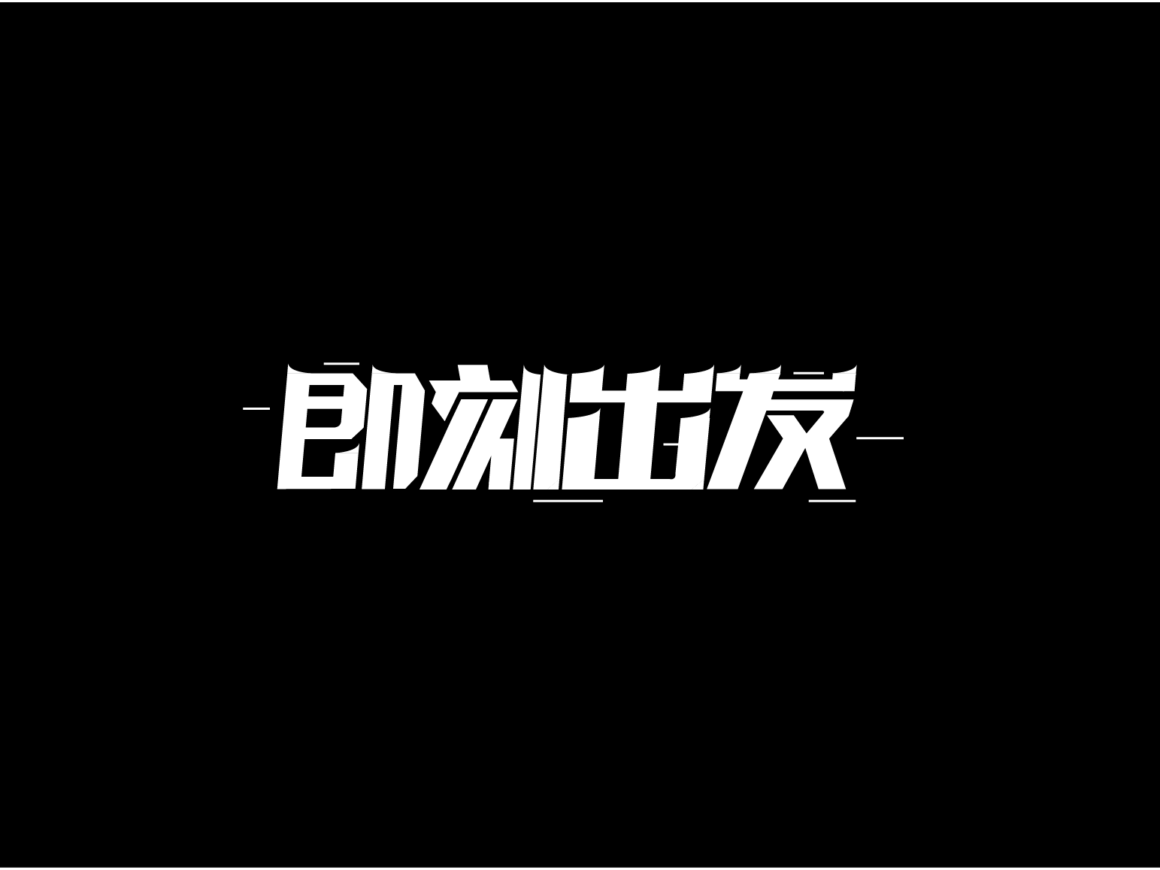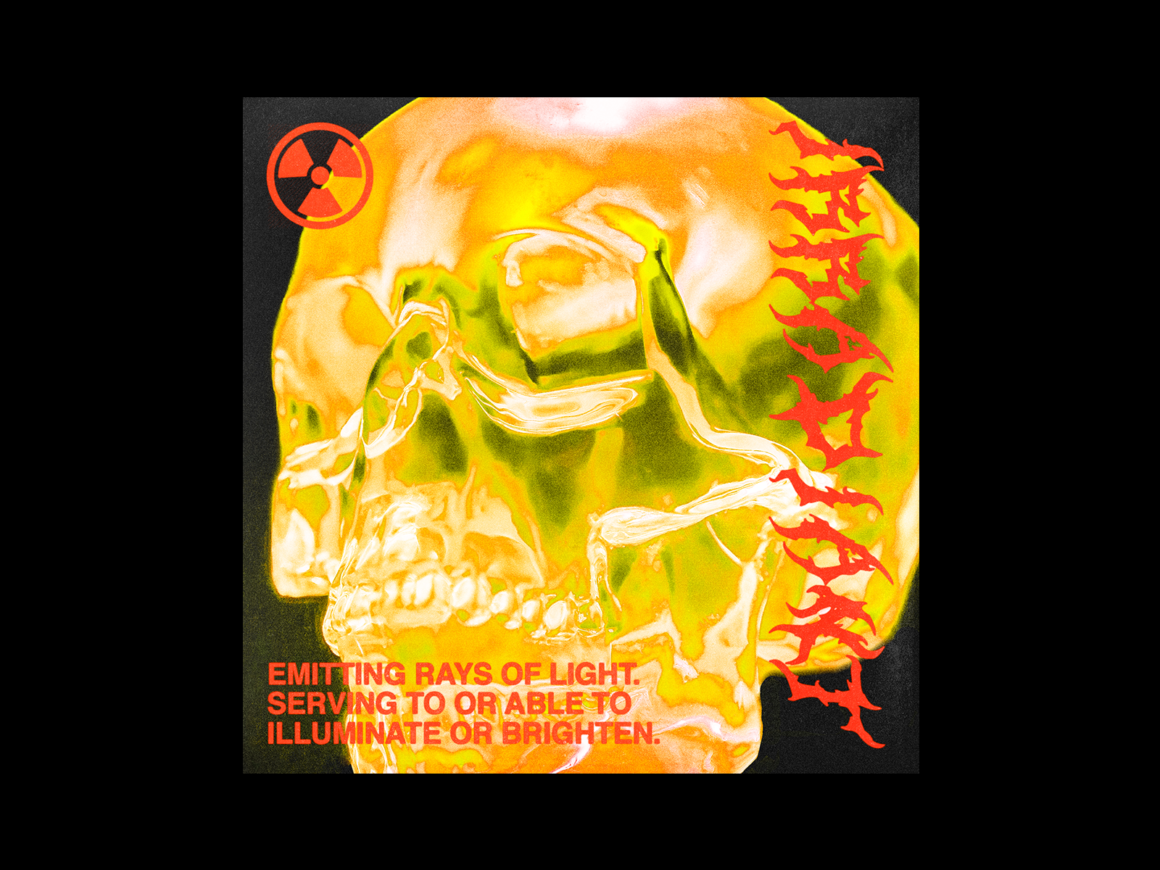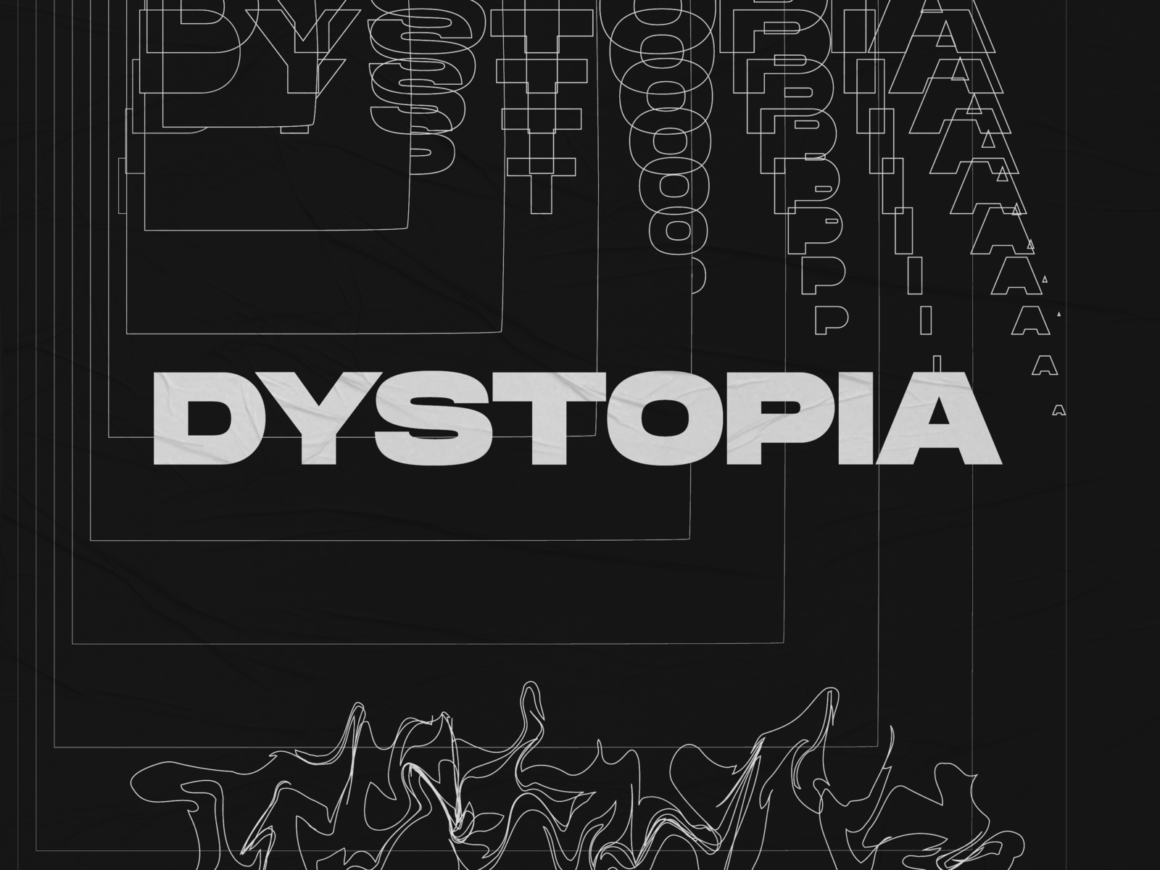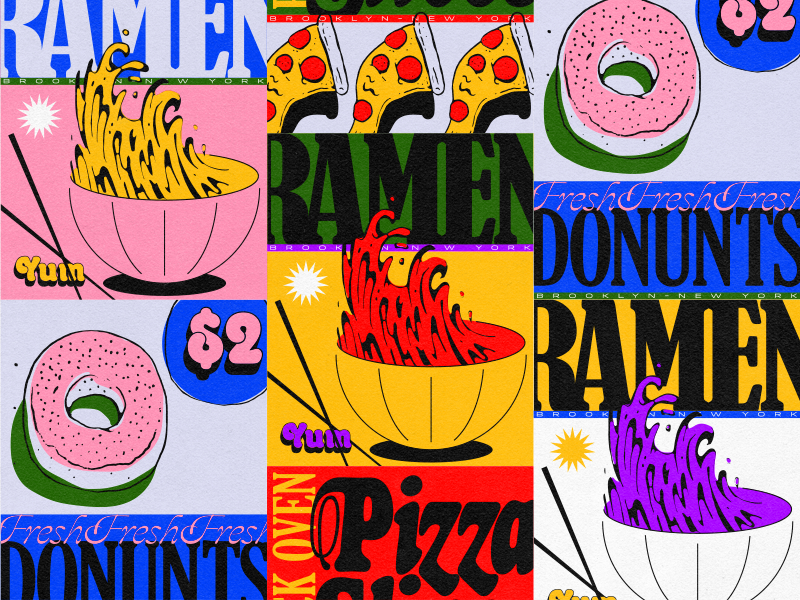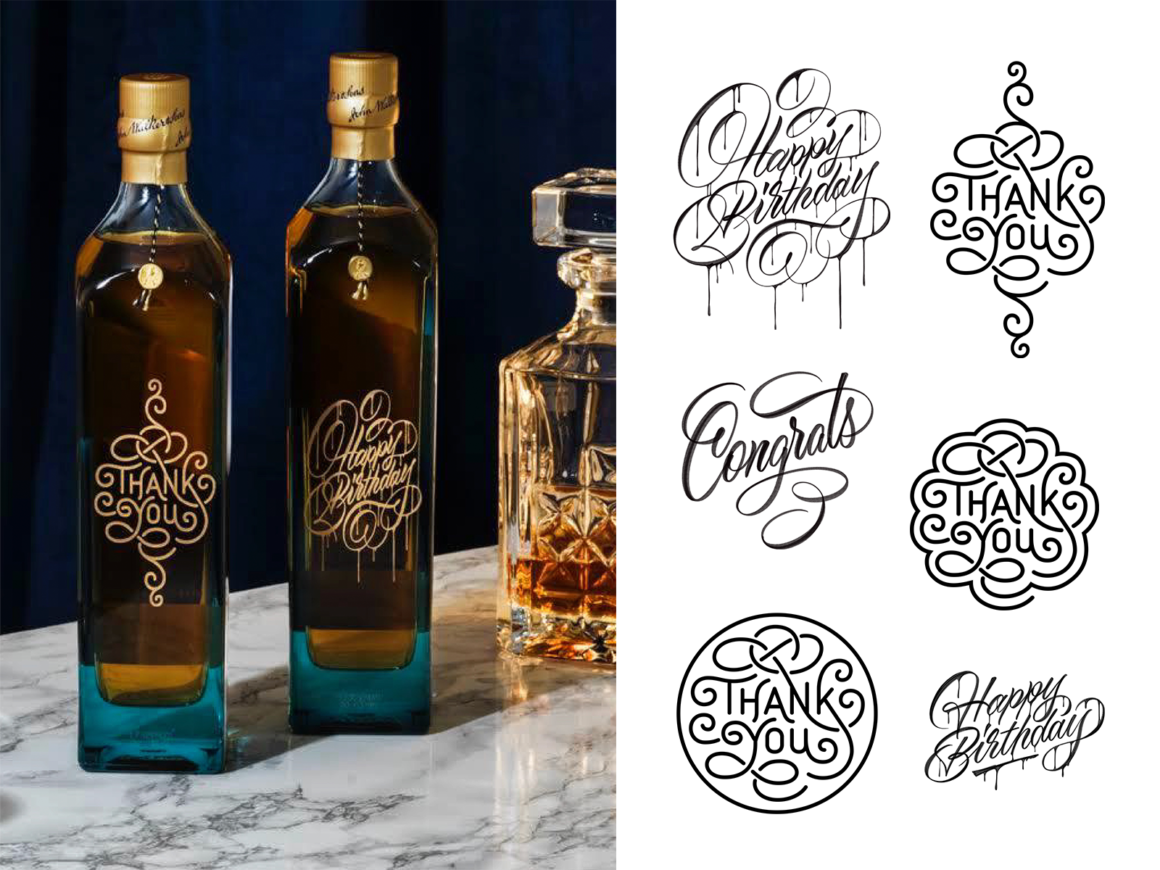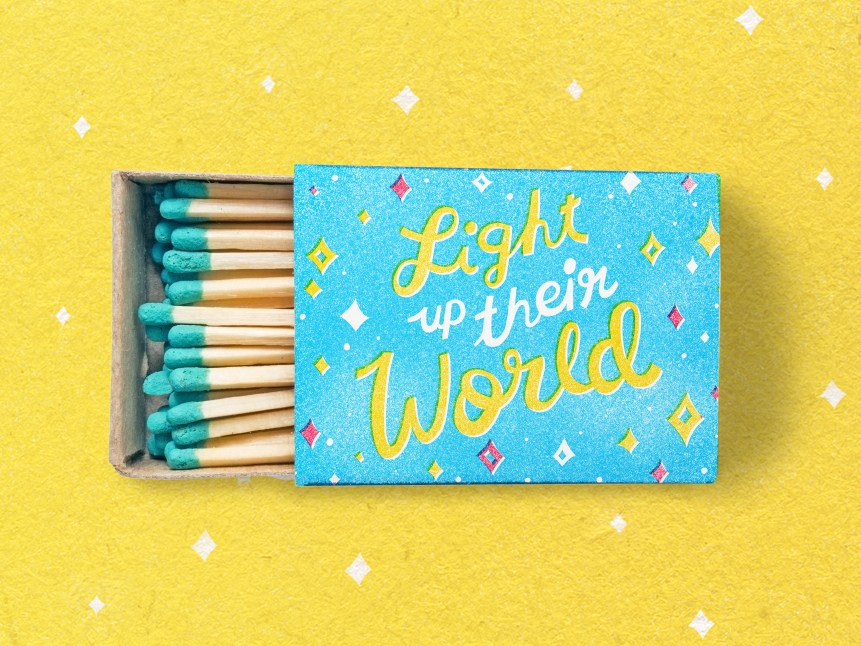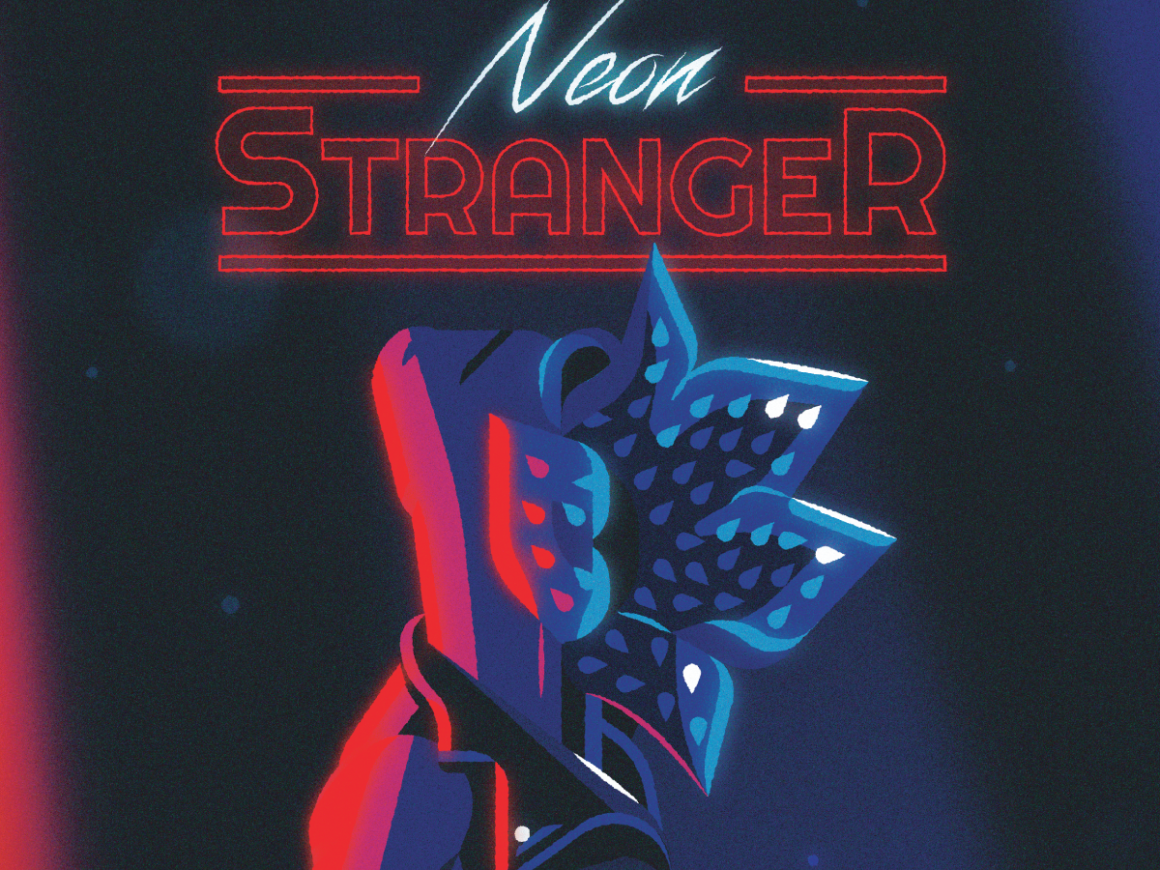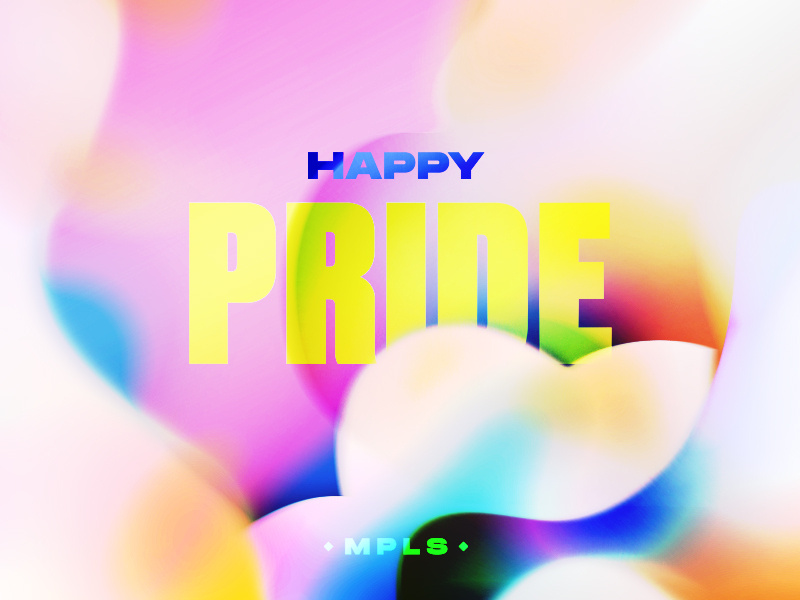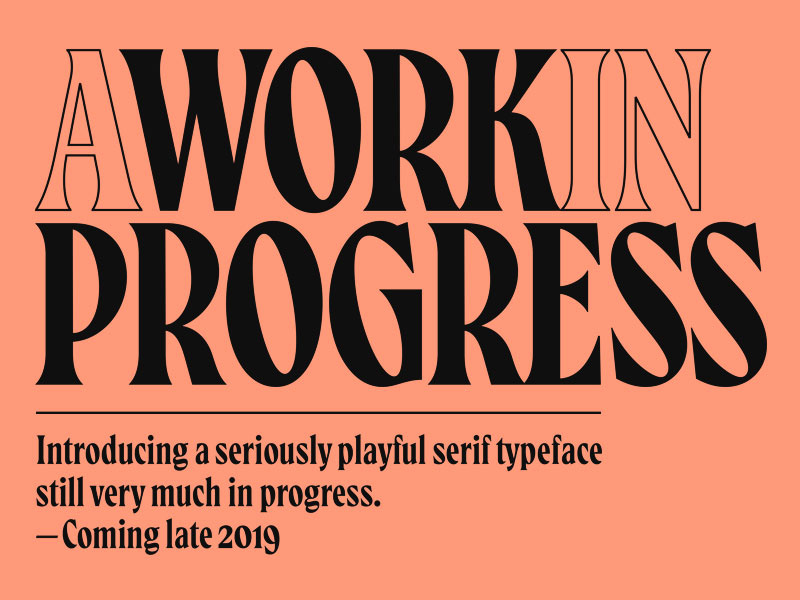
10 typographies créatives pour booster votre inspiration
La typographie est bien plus qu’un moyen de rédiger quelque chose. C’est un moyen de mettre en forme ce que l’on souhaite dire et appuie le message qu’on veut partager. Lors du choix de la typographie, il faut bien réfléchir à ce que cette dernière signifie. Tout simplement car une typographie en baton ne voudra pas dire la même chose qu’une typographie en brush ou en « hand writing ».
Aujourd’hui, je vous propose une série de 10 typographies créatives qui devraient vous aider à rendre vos créations, vos publications ou même votre CV plus élaboré.
1 – Dystopia par Brooke Chantrachuck
2 – Matchbox Lettering par Kelli Laderer
3 – A work in progress par Mark van Leeuwen
4 – Start at once par June
5 – Johnnie Walker Blue Label par Michael Moodie
6 – Happy Pride par Nancy McCabe
7 – NYC Food par Vincent Conti
8 – Space par Matt Pamer
9 – Irradiant par нαrry vιɴceɴт
10 – Neon Stranger par VISU∆L jams